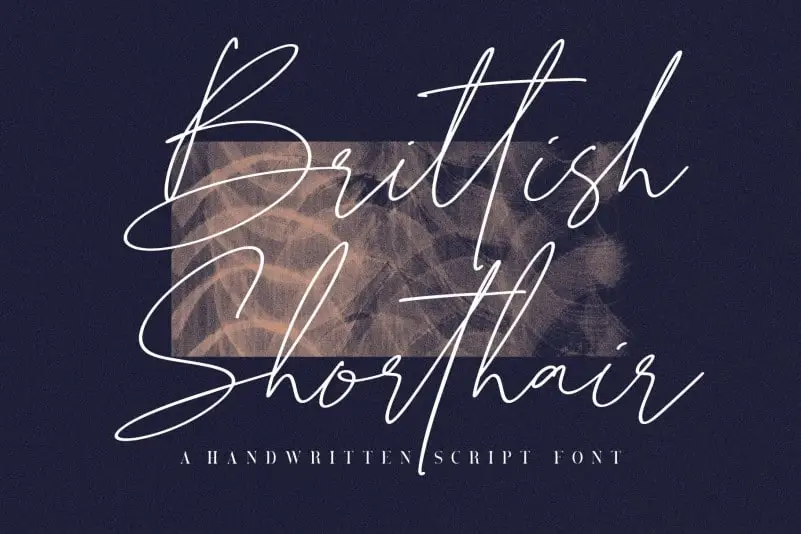
Brittish Sorthair Handwritten Font
Brittish Sorthair Handwritten Font é uma elegante fonte cursiva moderna criada pela equipe do Hanzel Space. Suas linhas simples e curvas sofisticadas atraem os olhos com sua natureza encantadora. Este tipo de escrita personalizada apresenta um fluxo suave, como se fosse desenhado por mão humana. Com seu estilo elegante e elegante, Brittish Sorthair é perfeito para criar mensagens que expressam atenciosamente o espírito criativo e sofisticado. Seja para uso em designs de marca, cartões de convite ou qualquer tipo de arte digital, esta fonte será uma escolha conveniente e única, capaz de transmitir seu estilo pessoal e moderno de maneira autêntica.